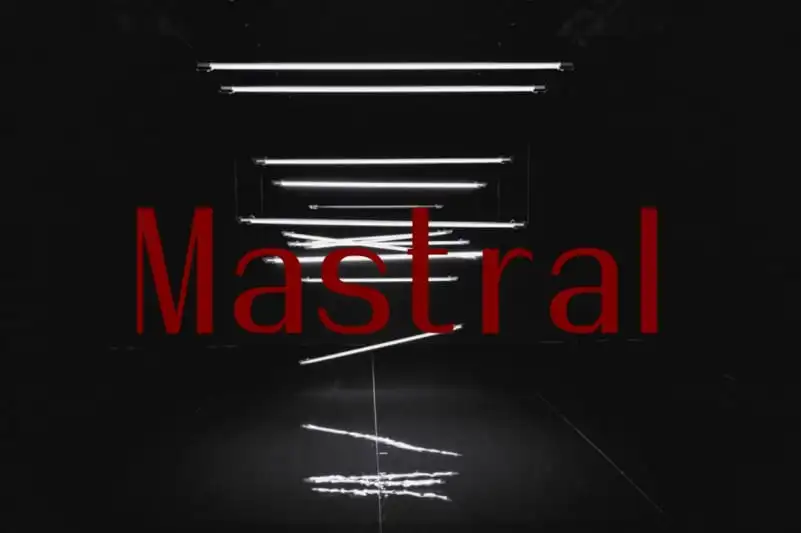
A fonte Mastral Sans Serif é uma elegante e moderna sans serif que traz a delicadeza do estilo francês. Ela foi criada e compartilhada por Arief Rochman, um designer gráfico talentoso de 99designs. Esta fonte não é uma serif typeface, mas sim um tipo sans serif que exala elegância. O design simples da Mastral está perfeitamente adaptado para ambientes de design minimalista e simples. Ela se destaca em projetos digitais, como sites e aplicativos, trazendo alegria aos textos com sua tipografia limpa e moderna. A Mastral Sans Serif é uma opção ideal para quem busca um estilo sofisticado sem perder o brilho de uma fonte sans serif. É perfeita para aplicações que buscam unir elegância e simplicidade, seja no design editorial ou em projetos digitais.